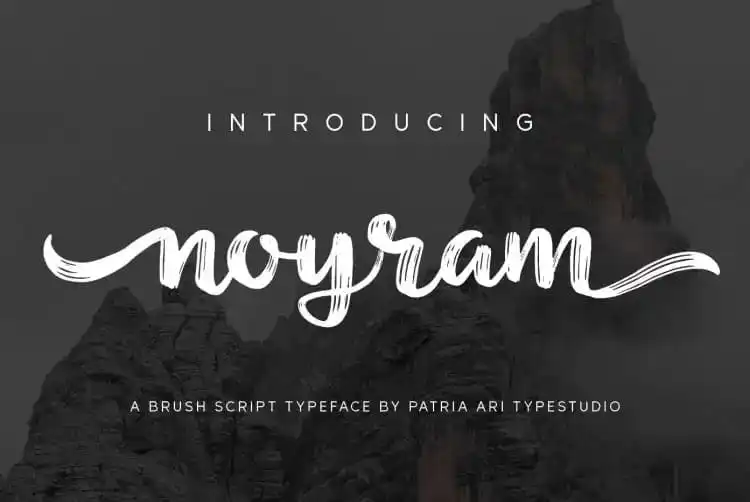
Noyram Script Font é uma fonte realista criada pela Patria Ari Typestudio, utilizando a técnica de traçado com pincel natural e autêntico. Esta fonte oferece alternativas, ligaturas e swashes para tornar o processo de design ainda mais versátil. Com textura fresca e estilizada, Noyram Script é perfeito para criação de logomarcas e letra à mão dourada. Ideal para projetos de branding, identidade visual, postagens nas mídias sociais, anúncios, embalagens de produtos, designs de produtos e etiquetas. Além disso, ela se adapta perfeitamente a qualquer tipo de projeto que você esteja trabalhando em. Engane-se quando pensa na Noyram Script: uma fonte versátil para tornar seu design mais criativo e atrativo.